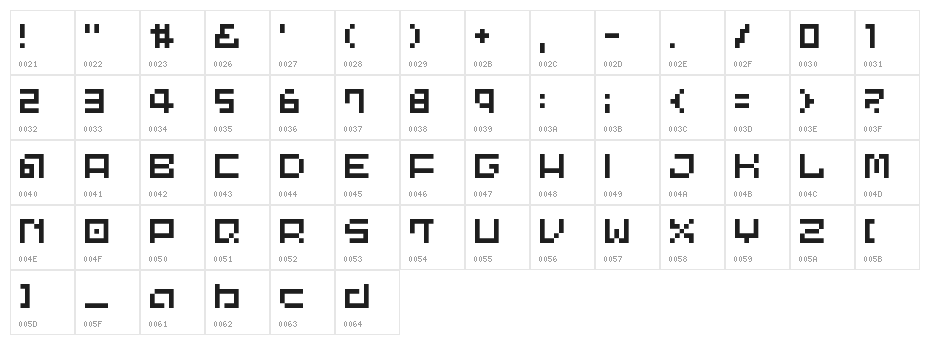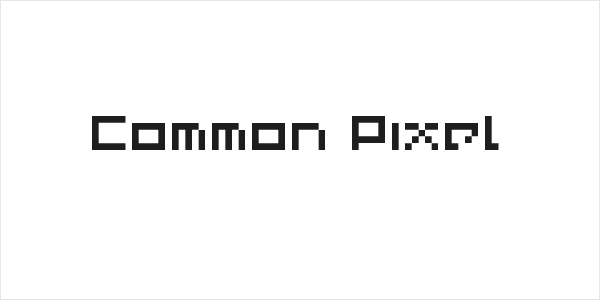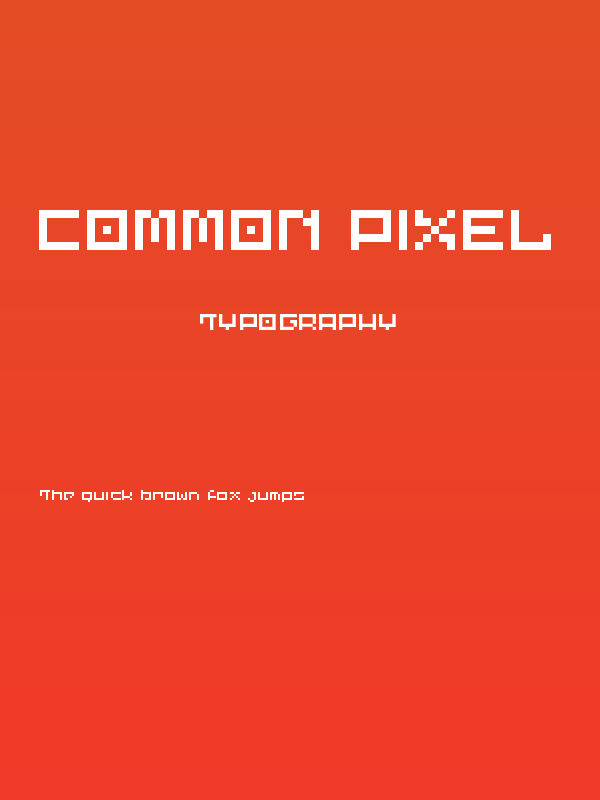
Common Pixel Font
| Kategorien | Pixel |
| Gesamtstil | Vintage |
| Anwendungsfall | Logos, Headlines, Digital Art |
| Vorgeschlagene Projekte | Ideal for retro video game designs, digital art projects, tech-themed posters, and any creative work that requires a nostalgic digital touch. |